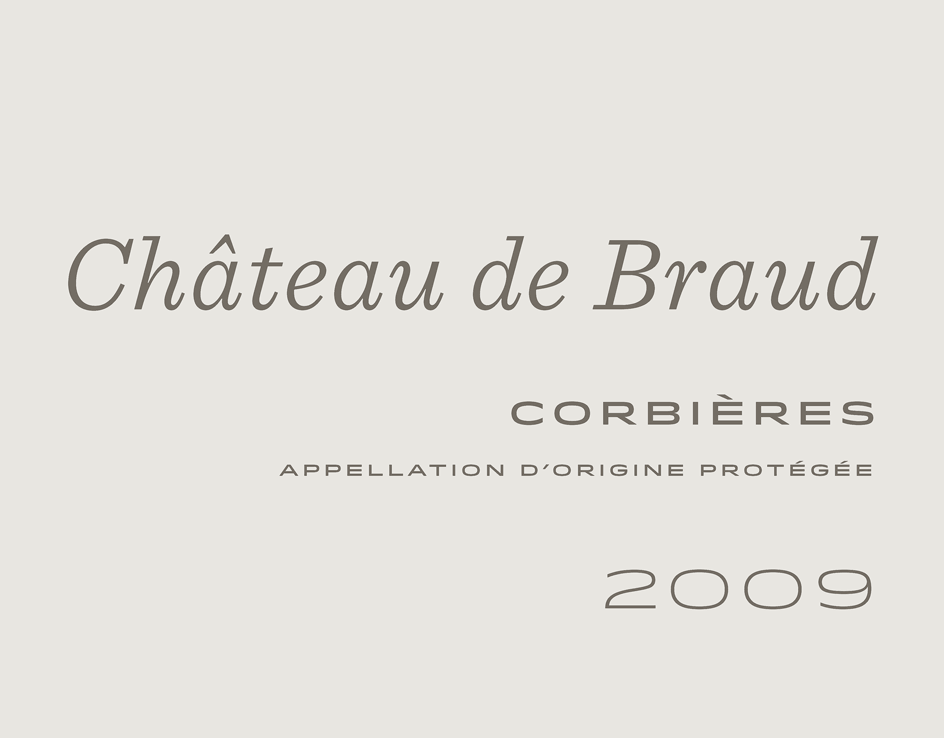
Sentinel und Idlewild?
bei der Suche nach Alternativen zur Vollkorn bold und Proxima Nova regular bin ich auf die Sentinel und Idlewild von H&FJ gestoßen – und bin begeistert! Da ich jedoch weder die eine noch die andere besitze und mir die Vorschau-Option nicht wirklich bei der Entscheidung weiterhilft, will ich euch nach eurer Meinung Fragen :nicken: .
Nach diesem Schema sollten sie gesetzt werden:
(Bitte nicht am Kerning und den Rändern stören, dient nur zur Verdeutlichung)
Was meint Ihr? Kann man die Sentinel und Idlewild so setzen? Oder sind sie zu eigenwillig und konkurrieren zu stark?
passt schon.ich würde dafür aber keine idlewild lizensieren, zumal die nicht preiswert ist.
da gibt es tausende andere fonts die einen ähnlichen stil haben, jedenfalls in diesem schnitt.
achso, jetzt sehe ich erst, die idelwild ist ja ein extended font, der nicht deinem gezeigtem beispiel entspricht.
das müsste man dann mal sehen ob das rein von der form passt, im grunde spricht aber nichts dagegen die
beiden zu mischen. aber auch hier... gibt es massig alternativen zur idlewild.
[…] das müsste man dann mal sehen ob das rein von der form passt […]
Genau diese Frage treibt mich um.
Ich sehe gerade auf der H&FJ-Seite ein Beispiel für die Kombination: